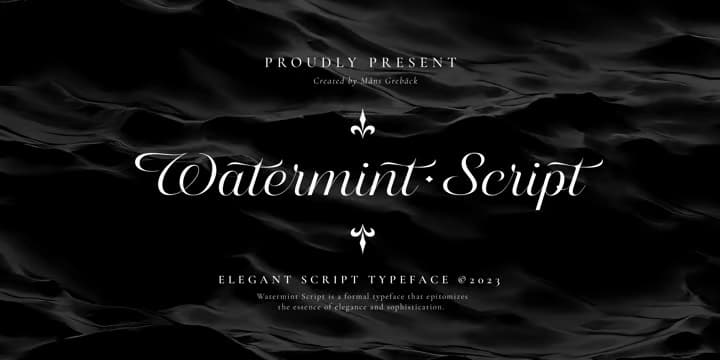
Watermint Script
優雅でかつ可愛らしいカッパープレート?スクリプト。一見クラシカルなカッパープレートのようでちょっと違う、活字イタリックとのハイブリッドのような書体でなかなかおもしろいスタイル。めずらしくxハイトが大きく、またカウンターも広めでゆったりと横幅があり、それが気取りすぎず可愛らしさを醸し出している。カッパープレートのエレガントさはちゃんと保っているので、招待状などにも使えると思う。やや傾きが強い Italic と2スタイルで2ウェイト。